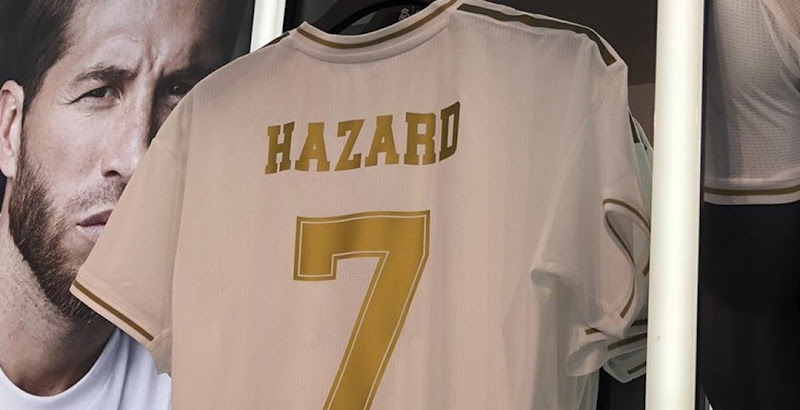
Ist Real Madrids 19-20 Heimtrikot-Schriftart Schlecht?
Vor ein paar Tagen präsentierte Real Madrid sein neues Trikot 2019/20 samt Schriftart. Das neue Adidas Real Madrid 2019-20 Trikot wurde von den Fans gut angenommen, aber die Schriftart war bei unseren Followern nicht sehr beliebt. Jetzt argumentierte sportsfonts.com, warum die neue Real Madrid 19-20 Schriftart für das Heimtrikot schlecht ist.
Real Madrid 2019-20 Trikot-Schriftart
Laut sportsfonts.com gibt es mehrere schlechte Eigenheiten an der Schriftart - sie würde nicht wirklich zu einem Fußballverein passen, da es ein US-Sportstil wäre, sie wäre nicht elegant und stilvoll genug für "Los Galacticos" und auch nicht einzigartig in der Welt des Fußballs. Andere Probleme, so sportsfonts.com, sind falsche Proportionen mehrerer Buchstaben und Zahlen.
Der Autor von sportsfonts.com, der deutsche Schriftingenieur Christoph Koeberlin, schlug ebenfalls eine korrigierte Version der Adidas Real Madrid 19-20 Trikot-Schriftart vor.
Die Real Madrid 2019-2020 Schriftart wird für alle Real-Trikots der Saison 2019/20 verwendet, nur in verschiedenen Farben. In der Liga wird Real Madrid, wie alle anderen 19 Mannschaften auch, eine einheitliche Schriftart verwenden.